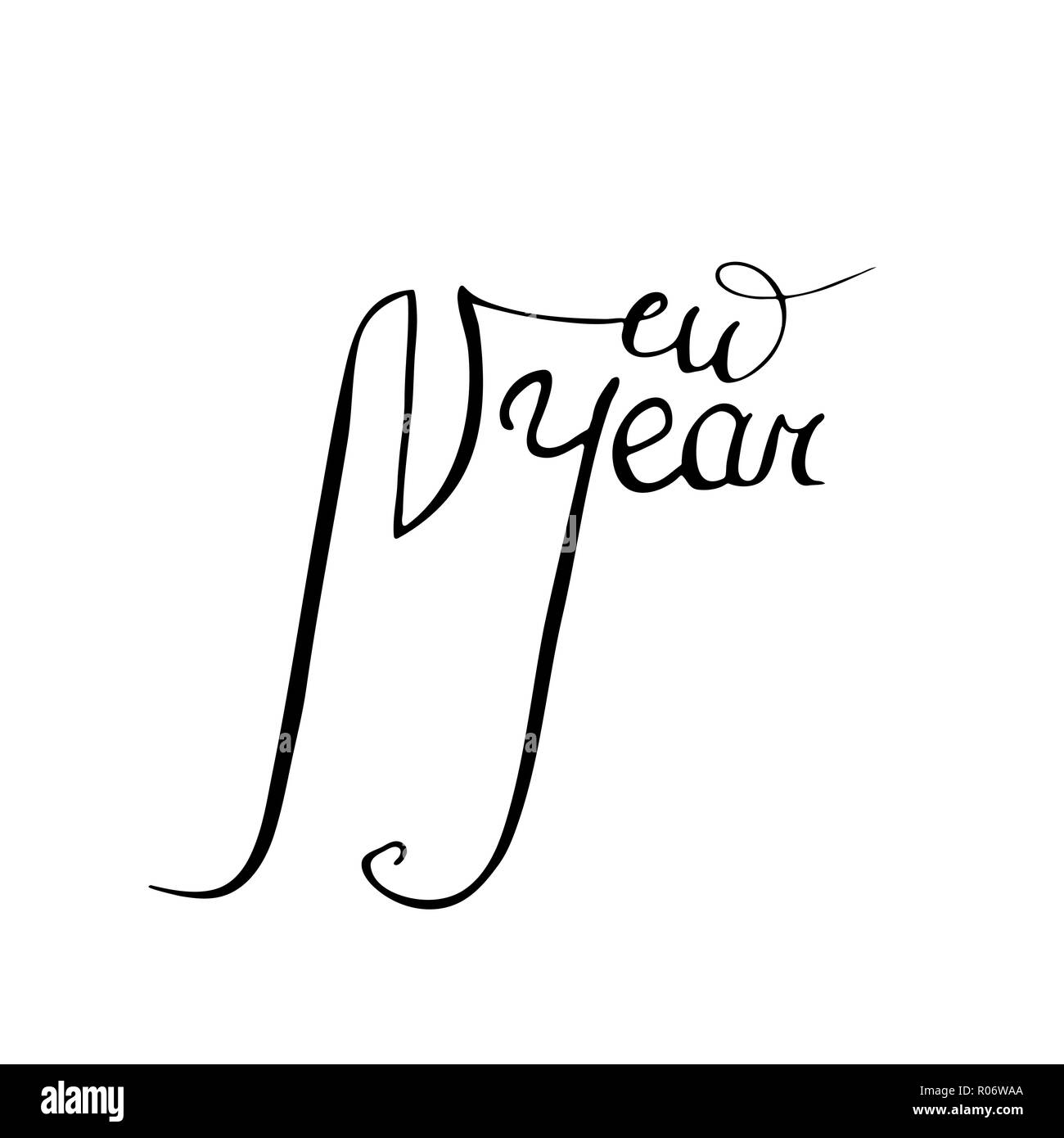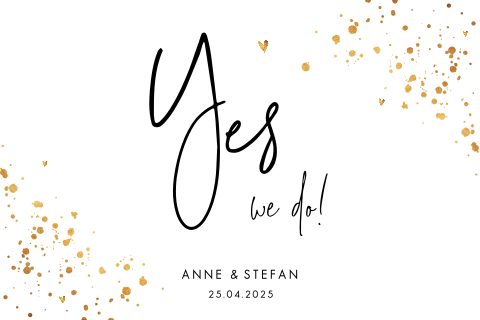
44 Kalligraphie Schriftarten Schöne Schriftarten
Kalligraphie schriftarten schöne schriftarten. Weitere ideen zu lettering buchstaben schriftarten schöne schrift. The blog does have other really great resources though. Wir stellen dir 23 schöne und kostenfreie kalligraphie schriftarten vor die du direkt in canva nutzen kannst von simpel bis verschnörkelt zierlich bis auffällig traditionell bis modern.
Kalligraphie schriftarten sind ideal als blickfang und eignen sich vor allem in überschriften oder als statement schriftart. Mit dem schriftgenerator schreibst du nachrichten texte nicht nur fett kursiv oder durchgestrichen sondern auch mit geschwungener schrift und vielen anderen verrückten fonts styles. Die kunst des schönschreibens liegt nach wie vor im trend weshalb sich kalligraphie schriftarten in vielen bereichen großer beliebtheit erfreuen.